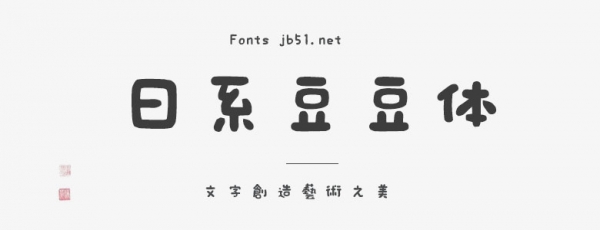
日系豆豆體(えるまー ElmerFont)就像用魔法筆寫的手寫字體。字體的風(fēng)格圓滾滾的,就像豆豆一樣可愛,特別適合用于女性,嬰兒,兒童,偏可愛風(fēng)格的海報(bào)設(shè)計(jì)??梢宰鳛闃?biāo)題文字和印刷物等的素材使用。這款字體雖然發(fā)布的時(shí)間比較久遠(yuǎn),最早發(fā)布于2006年,但是字體卻是永不過時(shí)的。這款字體是日本的設(shè)計(jì)師發(fā)布的字體,所以字符是以JIS為標(biāo)準(zhǔn)的,所以對(duì)繁體支持較好,簡體字相對(duì)少一些。